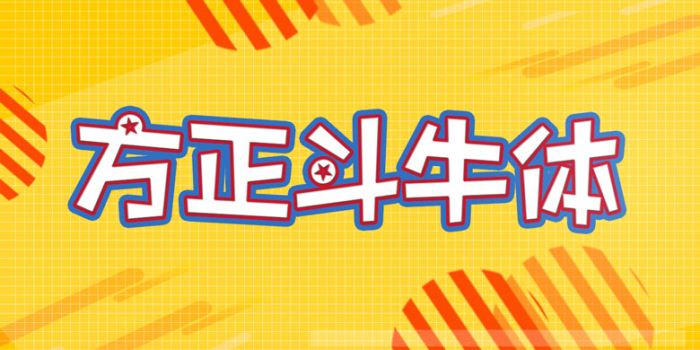
方正斗牛體家族由方正字庫(kù)郭炳權(quán)設(shè)計(jì)師出品的藝術(shù)字體,這款字體擁有八款粗細(xì)不同的字重,以星星元素作為點(diǎn)綴,具有很好的視覺感,適合應(yīng)用于藝術(shù)設(shè)計(jì)、平面宣傳設(shè)計(jì)、網(wǎng)頁(yè)設(shè)計(jì),書法等領(lǐng)域。
斗牛體的設(shè)計(jì)靈感源于西班牙精彩斗牛表演,五角星元素代表著對(duì)斗牛勇士必勝的祝愿。整體風(fēng)格硬朗有力、生動(dòng)有趣且酷勁十足。方正斗牛體家族包含8種字重,尤其適合時(shí)尚、體育、競(jìng)技、健身等領(lǐng)域的商業(yè)宣傳使用。